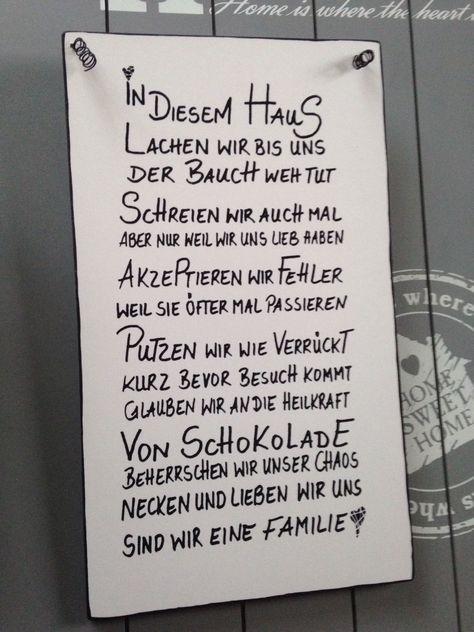
Welche Schriftart ist das?
weiß jemand was das für eine Schriftart ist ?
Ich hätte das gerne als Wandtatoo aber leider gibt es das nur als Schild.. Muss es also irgendwie selber gestalten aber jeder Schrift die ich ausprobiert habe passt nicht...
das ist keine digitale Schriftart; der Text ist mit der Hand geschieben. Wenn Du die einzelnen Buchstabenformen miteinander vergleichst, wirst Du feststellen, dass sie alle unterschiedlich sind. :-D